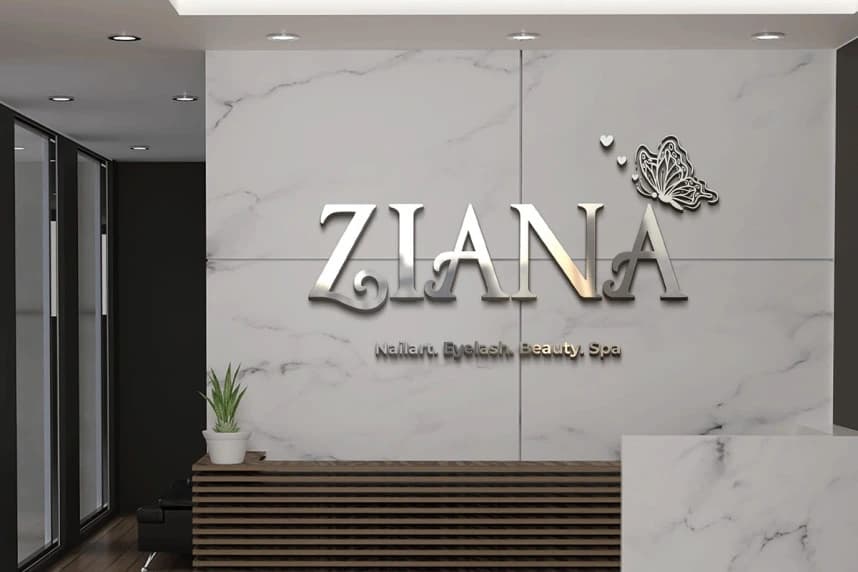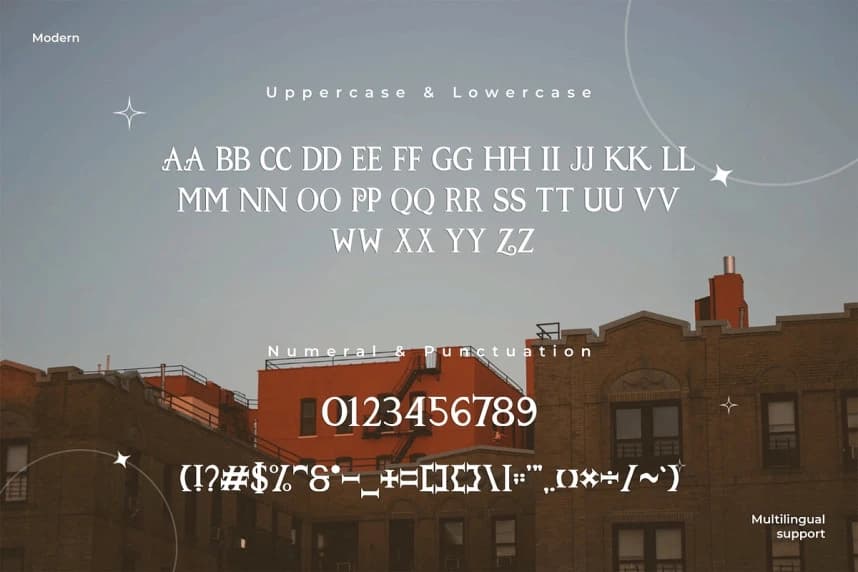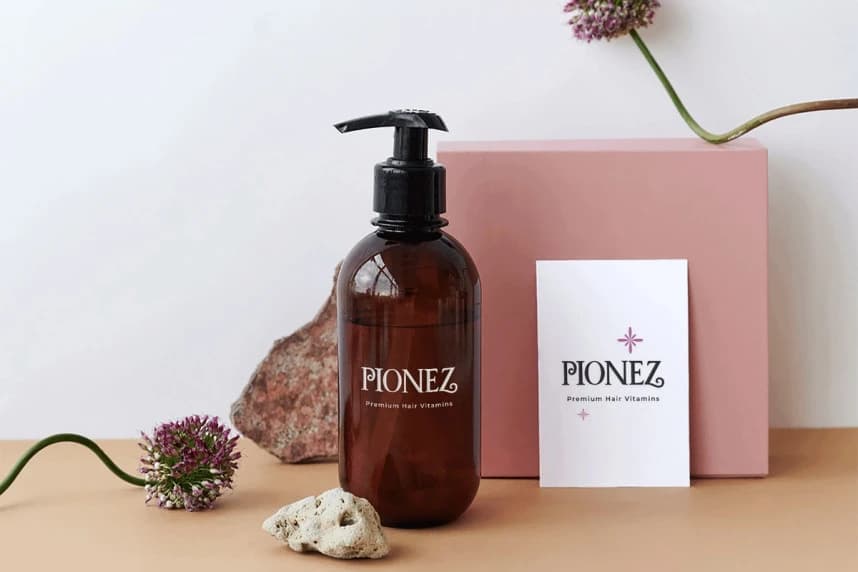
Zovaline Yazı Tipi
Zovaline Font, yaratıcı projelerinizi zarafet dokunuşuyla yükseltmek için tasarlanmış modern ve şık bir serif yazı tipidir. Temiz hatlar, belirgin serifler ve rafine bir yapıya sahip olan Zovaline, çağdaş stil ile klasik zarafeti kusursuz bir şekilde birleştirir ve bu da yüksek sınıf tasarımlar için
Zovaline Font, modern ve zarif bir serif yazı tipi olup yaratıcı projelerinizi bir doz zarafetle yükseltmek için tasarlanmıştır. Temiz hatlar, belirgin serifler ve rafine bir yapı ile Zovaline, çağdaş tarzı klasik zarafetle sorunsuz bir şekilde birleştirerek üst düzey tasarımlar için ideal bir seçim haline getirir.